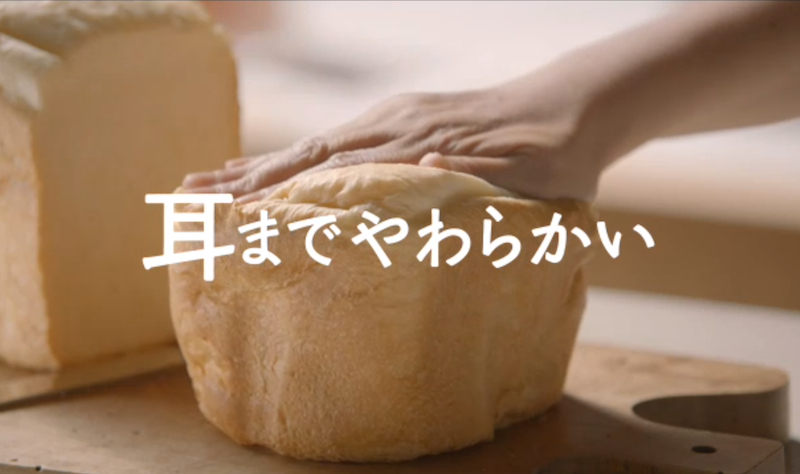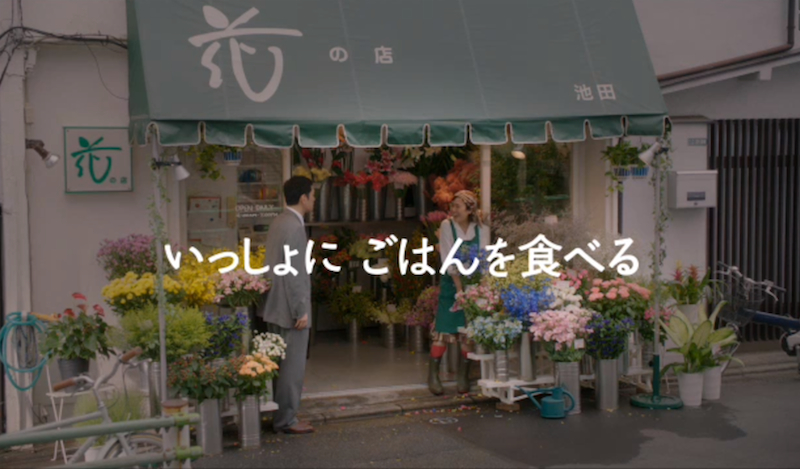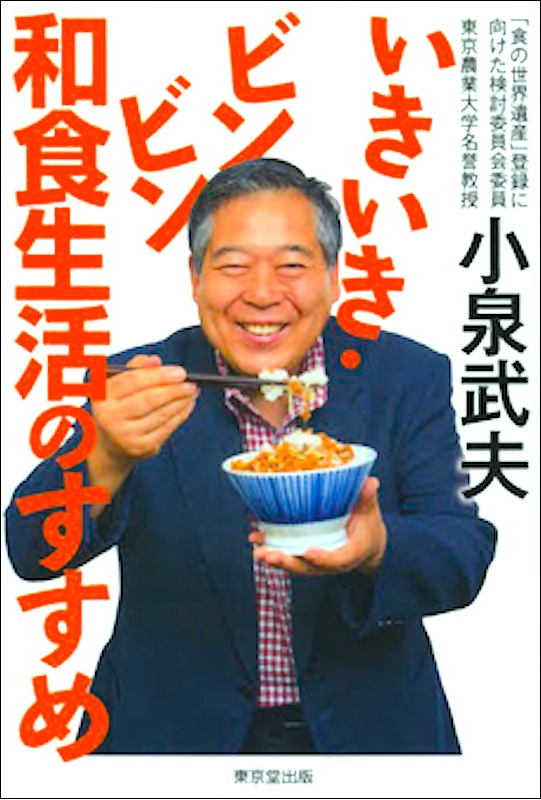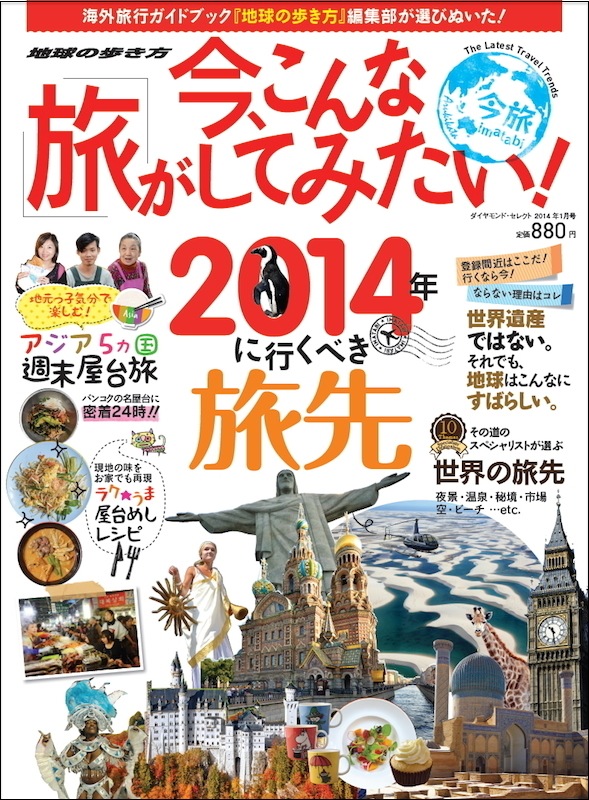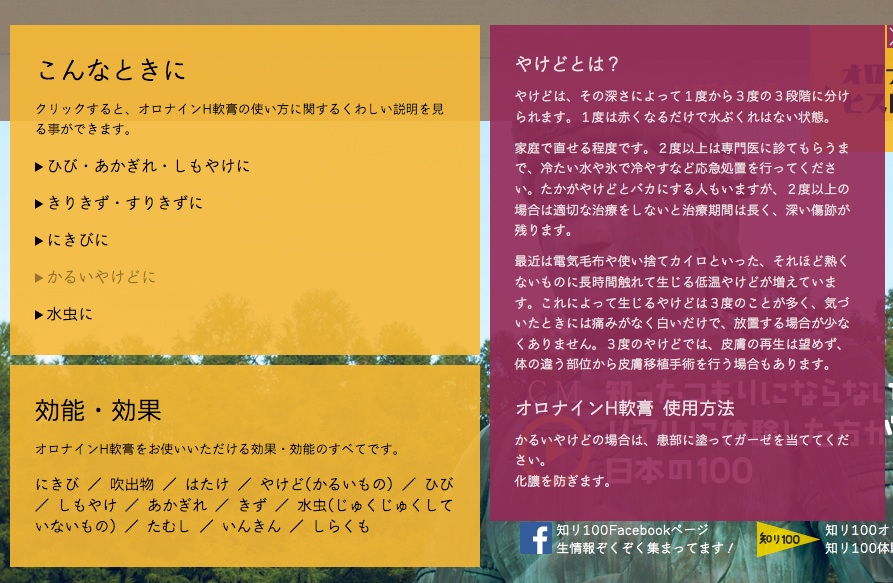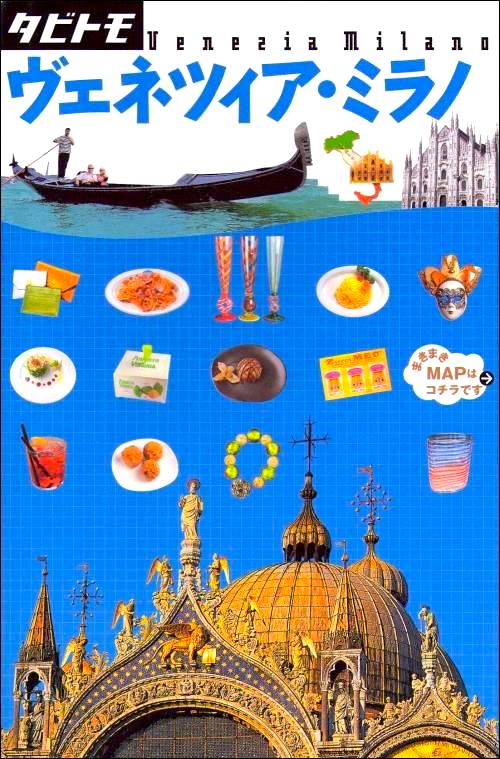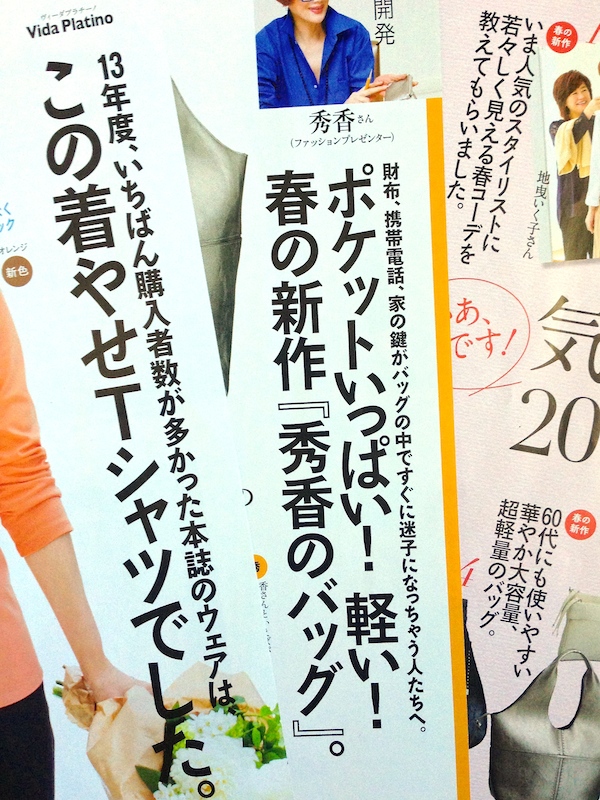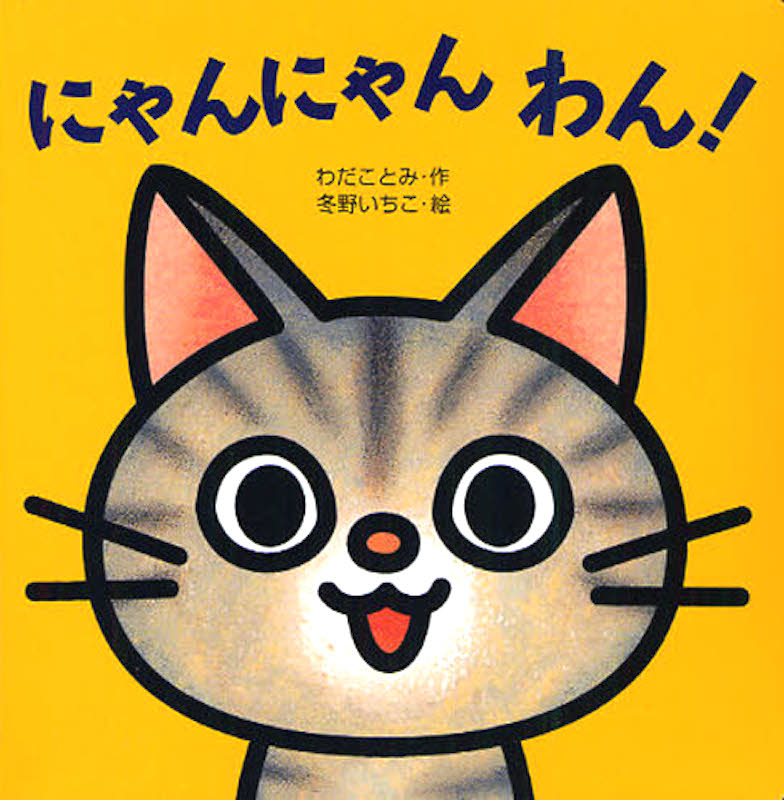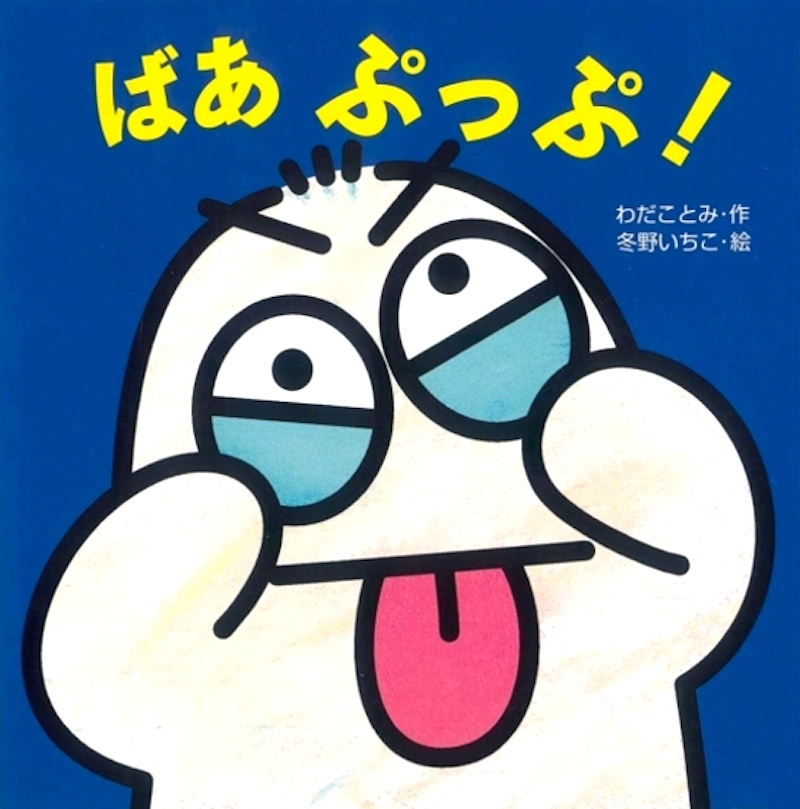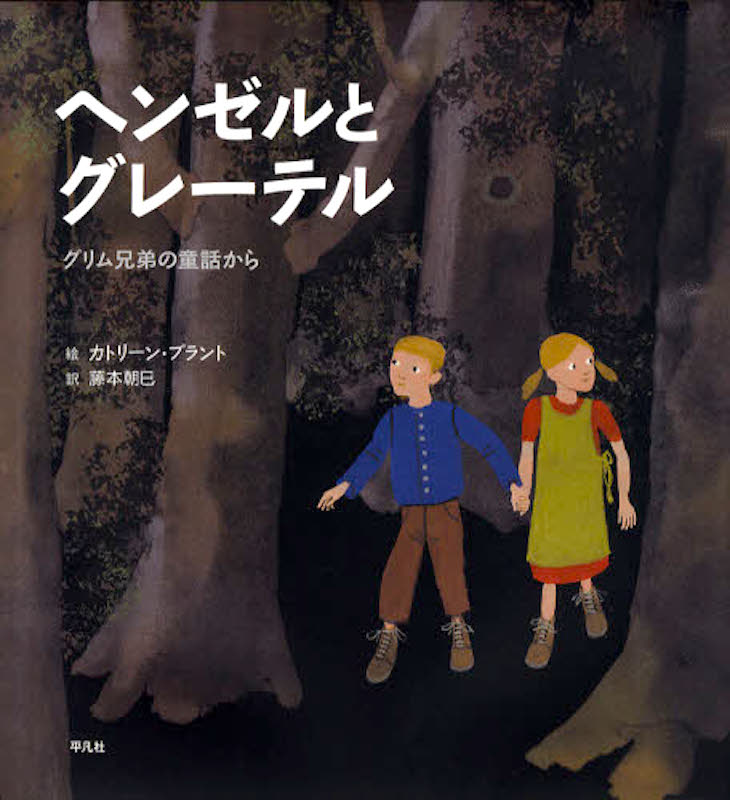
絵本の表紙  さとうゆたか  2015年11月21日(土) 15:14
書名:もしも暗闇がこわかったら夜空に星をくわえましょう
著者:クーパー・エデンズ、角田光代
発行:ほるぷ出版
もう1点。
書名:もしも空が落ちてきたら朝食に雲をいただきましょう
著者:クーパー・エデンズ、角田光代
発行:ほるぷ出版
本の表紙  さとうゆたか  2015年11月5日(木) 16:57
久しぶりに見た「墨東くずれ」。
さらに、かすれ加工されている。
書名:ブラックメイル 上 疑惑
著者:斎田 祐造
発行:文芸社
こちらは下巻。
記事の見出し  さとうゆたか  2015年10月31日(土) 10:56
通販雑誌の記事ページ。
映画の題名  さとうゆたか  2015年10月27日(火) 16:37
ボクは坊さん。
文字のカドは、丸く処理されている。
テレビCM  さとうゆたか  2015年10月12日(月) 22:29
象印、羽釜のごはん。15秒CM↓
もう1点。30秒CM↓
本の表紙  さとうゆたか  2015年10月7日(水) 14:26
書名:心をひらく あなたの人生を変える
著者:ジェームス・スキナー, 柴田博人
発行:PHP研究所
絵本の表紙  さとうゆたか  2015年9月28日(月) 11:15
書名:パパのカノジョは
著者: ジャニス・レヴィ, クリス・モンロー, もん
発行:岩崎書店
かな書体に墨東(あるいは墨東N)を採用した縦組み見出し・本文の書籍を見かける機会がなく残念に思います。
横組み本文見出し書体(かな)に使われている例を手に取ったのも今回が初めてです。
ケータイ〈万能〉フランス語入門:久松健一 著(HP欄は出版社紹介頁)
出版社公式サイトに本文見本はなく、高解像度画像で墨東仕様状況が確認出来るAmazonの「なか見!検索」は著作権保護コンテンツ管理下にあるため画像を添付出来ません。
この書体、かなり使われていると思いますが、書籍の本文ページは、なかなか画像アップしずらいですね…。
絵本の表紙  さとうゆたか  2015年9月18日(金) 11:13
書名:はずかしがりやのバナナくん
著者:岡田よしたか
発行:PHP研究所
本の表紙  さとうゆたか  2015年9月15日(火) 17:03
書名:同僚に知られずにこっそり出世する方法
著者:ブレンダン・リード
訳者:酒井 泰介
発行:ダイヤモンド社